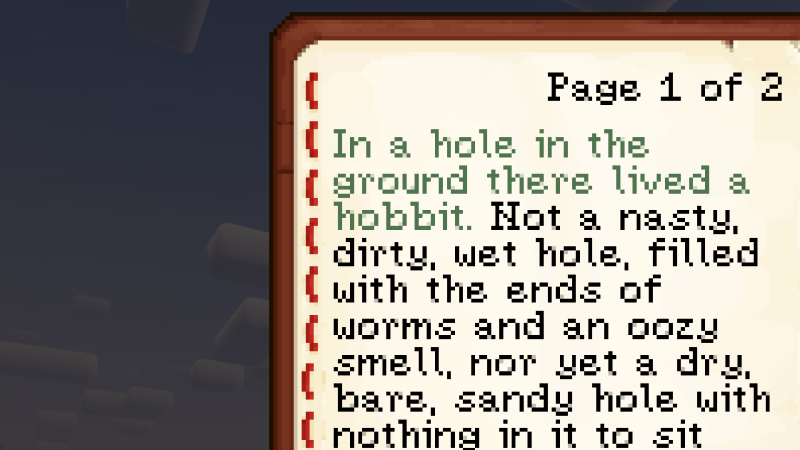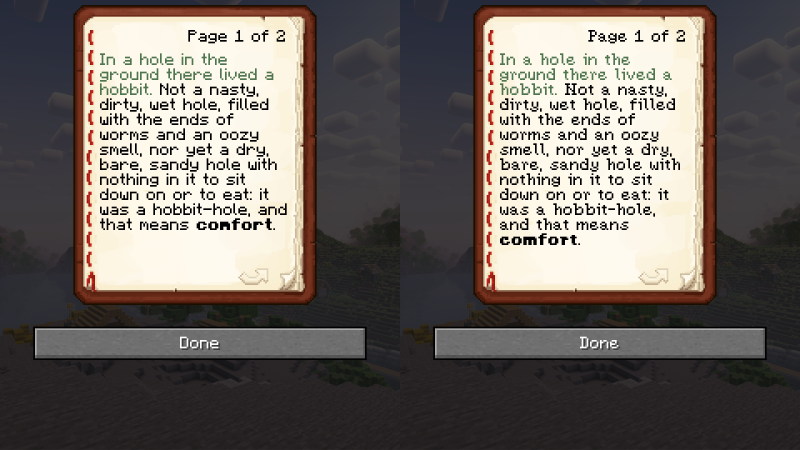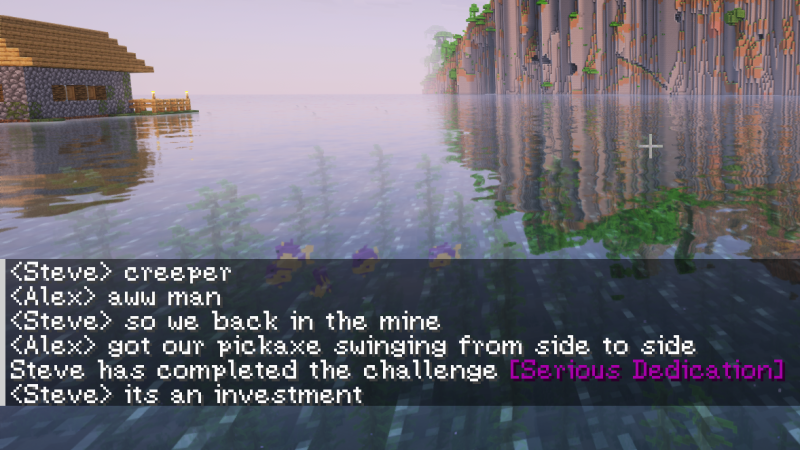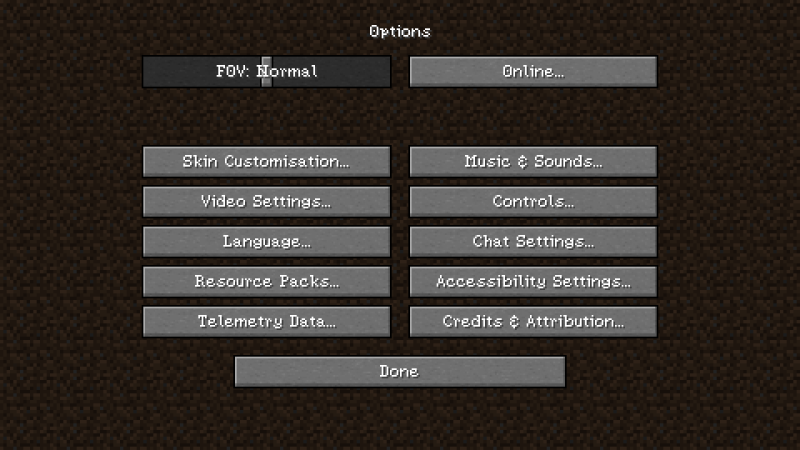
(Bee's) Serified Font 26.2/1.21.11 (шрифт, фэнтези, средневековье 16x)
Этот ресурспак полностью перерабатывает шрифт Minecraft, придавая ему более фэнтезийный и средневековый вид, соответствующий магической атмосфере игры. Текст становится более человечным и удобочитаемым.
Особенность пака — использование полупрозрачных пикселей для сглаживания (anti-aliasing). Результат может различаться в зависимости от вашего экрана. Обратите внимание: пока не поддерживаются диакритические знаки и акценты.